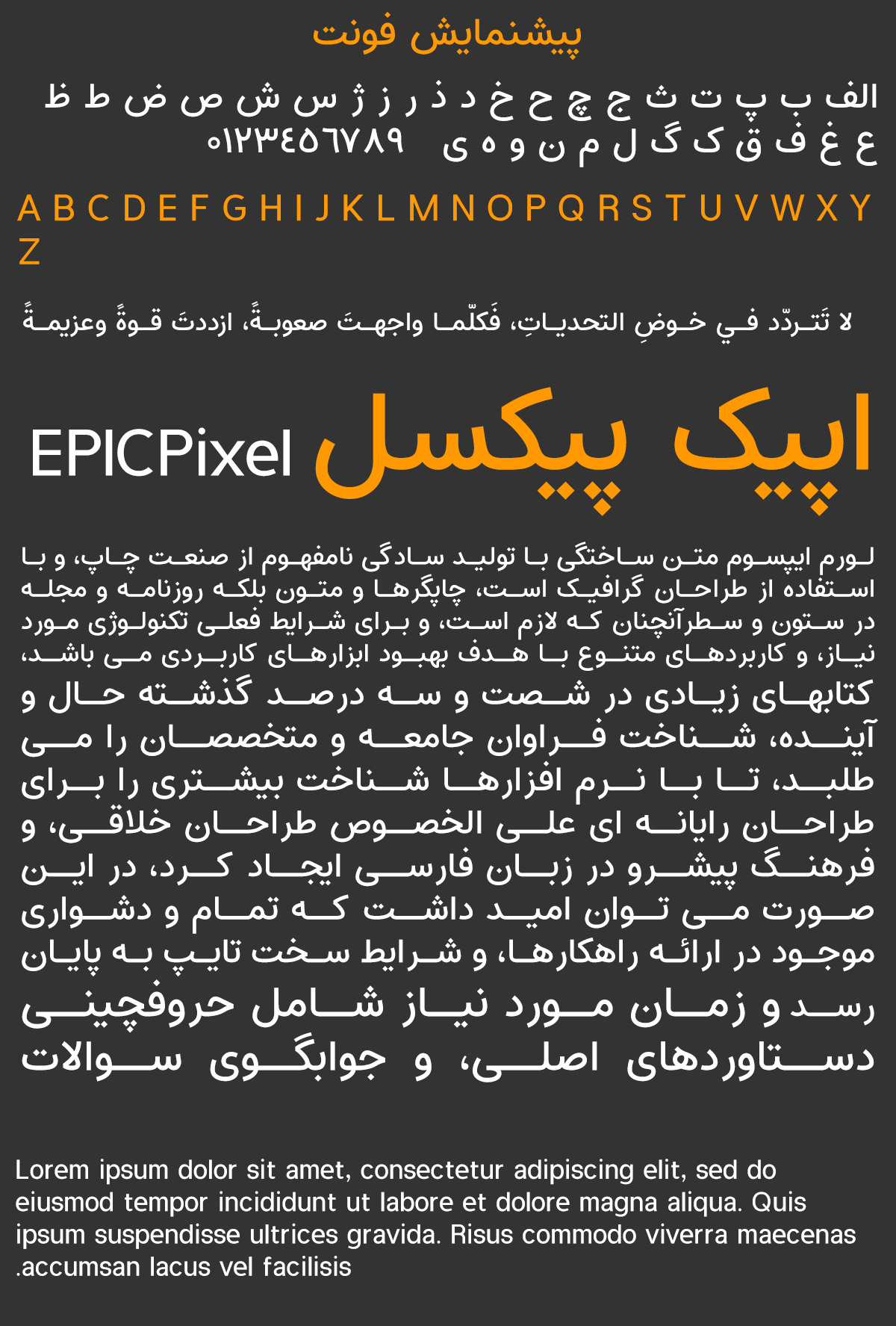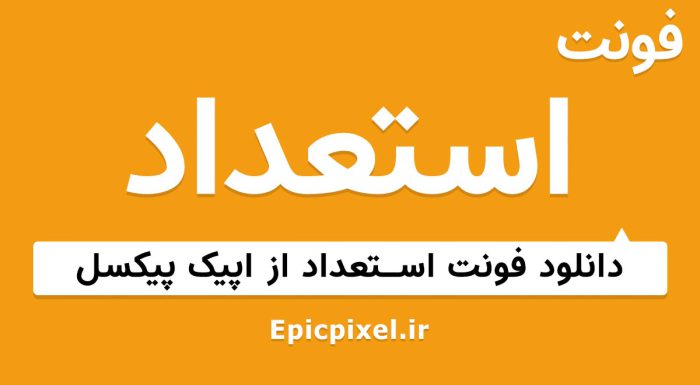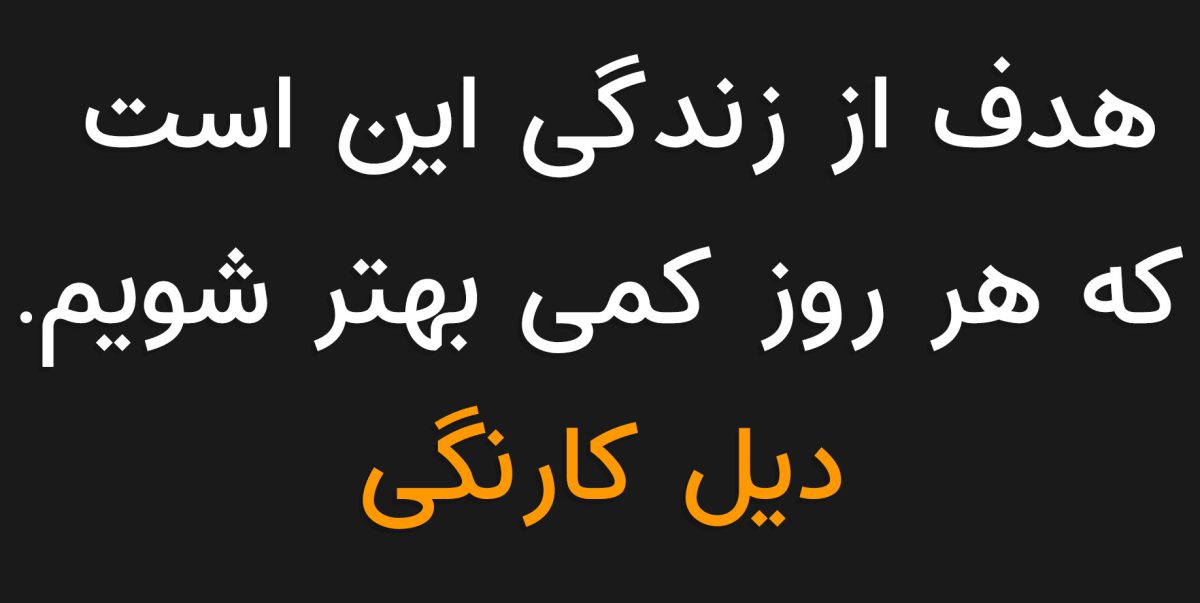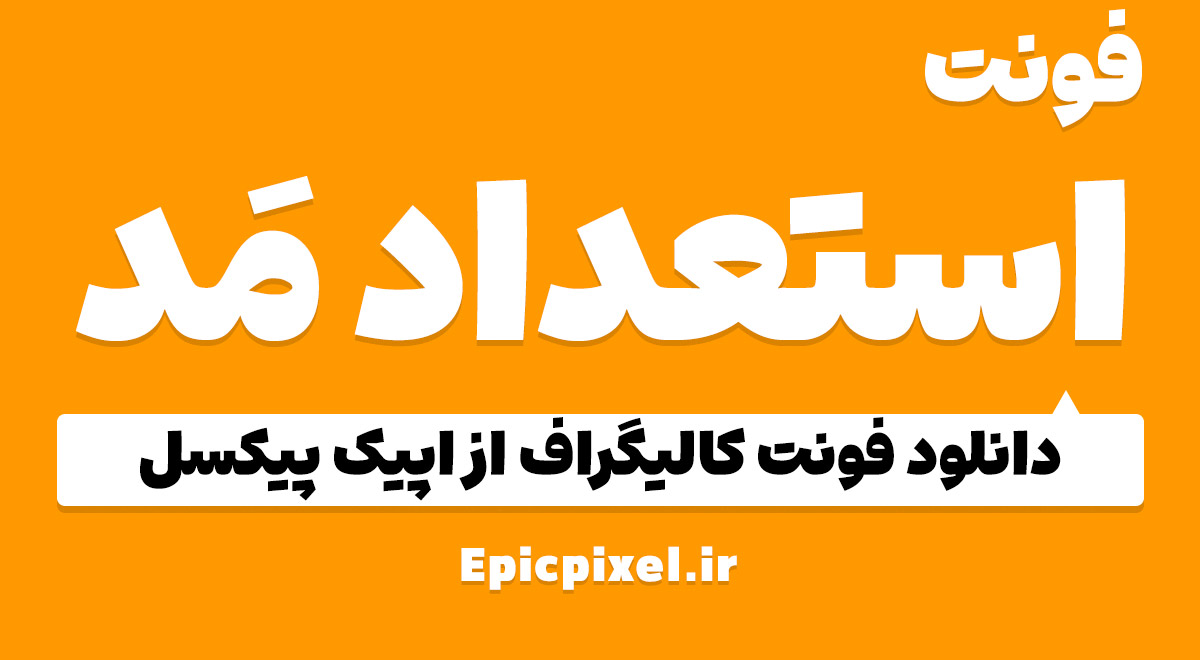
9 فونت استعداد فارسی Estedad
فونت استعداد فارسی (Estedad) یک قلم رایگان و مدرن است که در ۳ سبک اصلی ارائه می شود: استعداد اصلی (Estedad Original) با ۹ وزن و نسخه وریبل، استعداد نسخه ۲.۰ با ۵ وزن، و استعداد مد (Estedad Mad) تک وزن. این فونت که توسط امین عابدی طراحی شده، برای متون طولانی و عنوان مناسب است و در فرمت های TTF و WOFF2 در دسترس قرار می گیرد. استعداد از ارقام فارسی (FD Farsi Digits) پشتیبانی می کند و با طراحی تمیز بر پایه خط نسخ، برای طراحی وب، مطبوعات و رابط کاربری ایده آل است. این فونت علاوه بر فارسی، از زبان های عربی، لاتین و کوردی نیز پشتیبانی می کند.
فونت استعداد فارسی Estedad: قلم مدرن و رایگان برای متن و عنوان
فونت استعداد فارسی (Estedad)، یک فونت رایگان و همه کاره است که با هدف پاسخگویی به نیازهای طراحان در حوزه های مختلف، از جمله وب و چاپ، توسعه یافته است. این قلم توسط امین عابدی در سال ۱۳۹۶ (۲۰۱۷ میلادی) طراحی و منتشر شده است.
فونت استعداد در ۳ سبک اصلی ارائه می شود که هر کدام ویژگی های خاص خود را دارند:
- استعداد اصلی (Estedad Original) – نسخه ۷.۳: این نسخه کامل ترین بخش از خانواده استعداد است.
- ۹ وزن مختلف: از Estedad-Thin (نازک ترین) تا Estedad-Black (پررنگ ترین)، تمامی وزن ها شامل Estedad-Light, Estedad-ExtraLight, Estedad-Regular, Estedad-Medium, Estedad-SemiBold, Estedad-ExtraBold را پوشش می دهد.
- نسخه وریبل (Variable Font): این ویژگی به شما امکان می دهد تا به صورت پیوسته بین وزن ها تغییر ایجاد کنید و انعطاف پذیری بی نظیری در طراحی داشته باشید.
- نسخه FD Farsi Digits: این نسخه شامل ارقام فارسی است که برای متون فارسی بسیار کاربردی است.
- استعداد نسخه ۲.۰: این نسخه فشرده تر، شامل ۵ وزن اصلی است:
- Estedad Thin
- Estedad Light
- Estedad Medium
- Estedad Bold
- Estedad Black
- استعداد مد (Estedad Mad): این سبک، یک بازطراحی از تایپ فیس اصلی استعداد است که توسط محمد درویشی ساخته شده و به عنوان نسخه ای ضخیم تر و برجسته تر شناخته می شود.
- تک وزن: در یک وزن مشخص ارائه می شود.
- پشتیبانی: شامل نسخه فارسی دیجیتز و بدون حروف انگلیسی است، که آن را برای عناوین فارسی ایده آل می سازد.
طراحی و پشتیبانی زبان: فونت استعداد بر پایه خط نسخ طراحی شده است، اما با تغییرات هوشمندانه ای در زوایا، منحنی ها و چشمی حروف، ساختار نسخ گونه آن کمی کم رنگ تر شده و ظاهری مدرن تر به خود گرفته است. این طراحی یکپارچه در تمام وزن ها حفظ شده و آن را به گزینه ای عالی برای طراحی رابط کاربری (UI) تبدیل می کند. علاوه بر زبان فارسی، فونت استعداد از زبان های عربی، لاتین و کوردی نیز پشتیبانی می کند که امکان استفاده حرفه ای در پروژه های چندزبانه را فراهم می آورد.
کاربردهای فونت استعداد در طراحی های وب و چاپی
فونت استعداد فارسی (Estedad) با تنوع در وزن ها، پشتیبانی از فرمت های مختلف و طراحی مدرن و خوانا، یک انتخاب عالی برای طیف گسترده ای از کاربردها در طراحی گرافیک، وب و نشر است. این فونت رایگان و در دسترس، ابزاری قدرتمند برای طراحان است.
کاربردهای اصلی:
- طراحی وبسایت و رابط کاربری (UI/UX): به دلیل بهینه سازی برای وب (فرمت WOFF2) و خوانایی بالا در متون طولانی، استعداد گزینه ای بسیار مناسب برای متون اصلی، پاراگراف ها، و عناصر رابط کاربری در وبسایت ها و اپلیکیشن هاست. نسخه وریبل آن نیز امکانات بیشتری برای طراحی پویا فراهم می کند.
- مطبوعات و نشریات: قابلیت خوانایی بالا، وزن های متنوع و ساختار یکپارچه، فونت استعداد را برای استفاده در روزنامه ها، مجلات، کتاب ها و پایان نامه ها ایده آل می سازد، به خصوص برای متون طولانی.
- عنوان و تیتر: سبک استعداد مد (Estedad Mad) که نسخه ای ضخیم تر و برجسته تر است، به طور خاص برای تیترها، عناوین اصلی، و لوگو طراحی شده و می تواند به طرح شما گیرایی و جلوه ای منحصر به فرد ببخشد.
- پوستر و بنر تبلیغاتی: تمامی سبک های استعداد، به خصوص وزن های سنگین تر، برای طراحی پوسترها، بنرها و مواد تبلیغاتی مناسب هستند و می توانند پیام شما را به وضوح منتقل کنند.
- هویت برند و لوگو: با توجه به طراحی تمیز و مدرن، این فونت می تواند در طراحی هویت بصری و لوگو برای کسب وکارها و پروژه های مختلف به کار رود.
- پروژه های چندزبانه: پشتیبانی از زبان های فارسی، عربی، لاتین و کوردی، استعداد را به انتخابی عالی برای پروژه هایی تبدیل می کند که نیاز به هماهنگی بصری بین این زبان ها دارند.
فونت استعداد چه برای متون طولانی و چه برای عناوین برجسته، ساختاری حرفه ای و خوانایی بالایی را به طراحی های شما اضافه می کند.